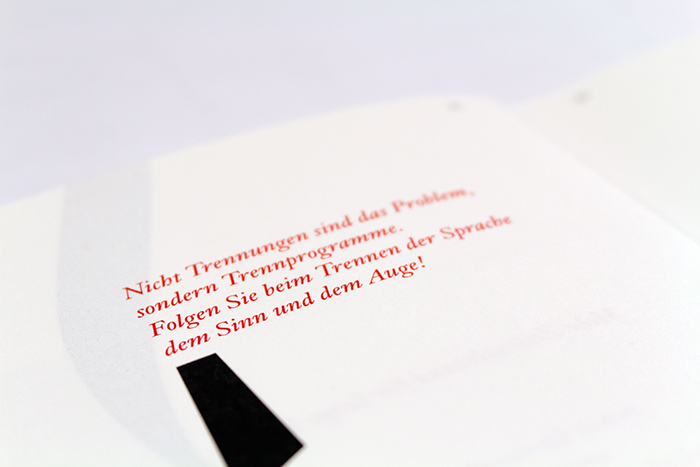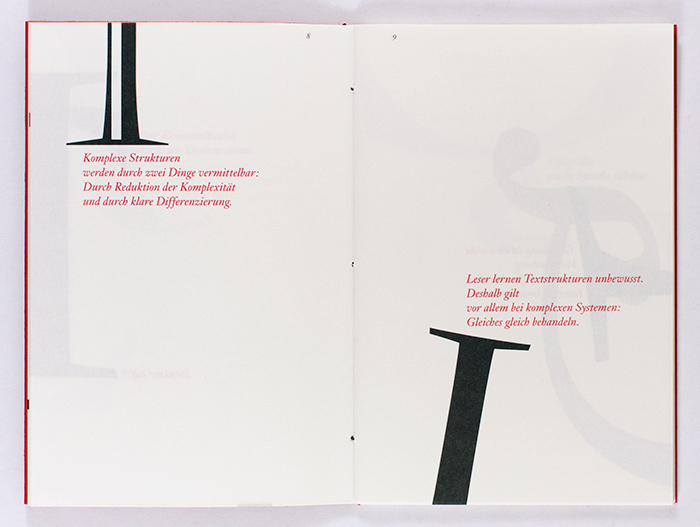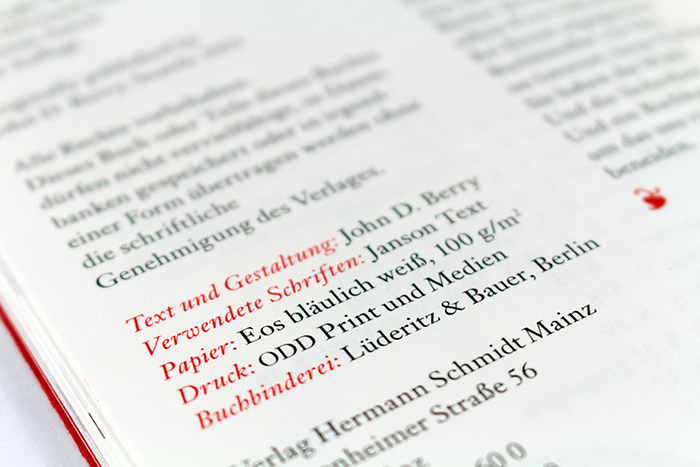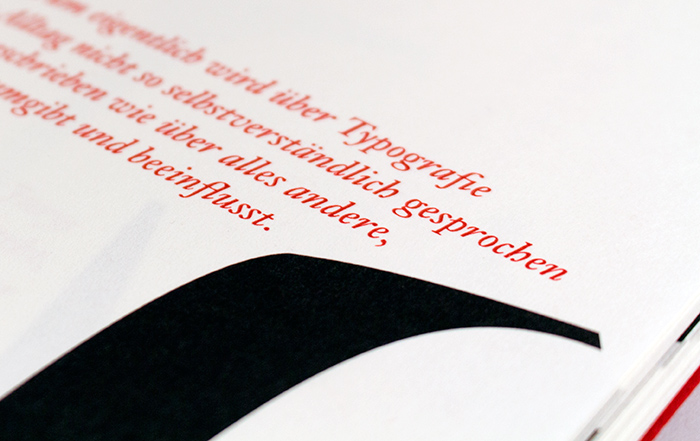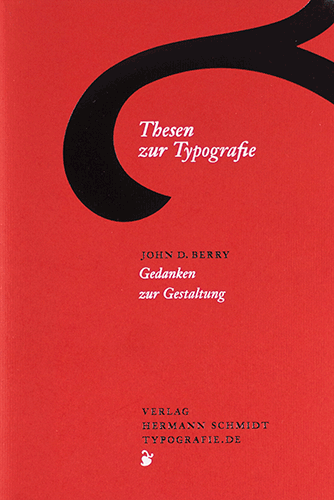
Thesen zur Typografie erschien 2014 im Verlag Hermann Schmidt Mainz. Es ist eine deutsche Ausgabe des 2013 erschienenen Hanging by a Serif von John D. Berry. Das circa 12 × 18 Zentimeter große fadengebundene Heft präsentiert Zitate Berrys, die sich mit Typografie und Design beschäftigen. Den in Janson-Antiqua gesetzten Texten werden große Serifen-Darstellungen verschiedenen Schriften als Gestaltungselement der Doppelseiten gegenübergestellt. Zitate wie »Klare Kommunikation setzt klares Denken voraus« oder »Lesbarkeit hängt auch immer vom Umfeld« sind eher sachlich-pragmatisch. Berry drückt sich nicht so wortgewaltig und tiefsinnig wie Weidemann oder so provozierend wie Tschichold aus. Alles in allem ist Thesen zur Typografie mit einem Verkaufspreis von 9,80 Euro aber ein passables Heft zum Verschenken an Freunde und Lieberhaber der Schrift.
Untertitel: Gedanken zur Gestaltung